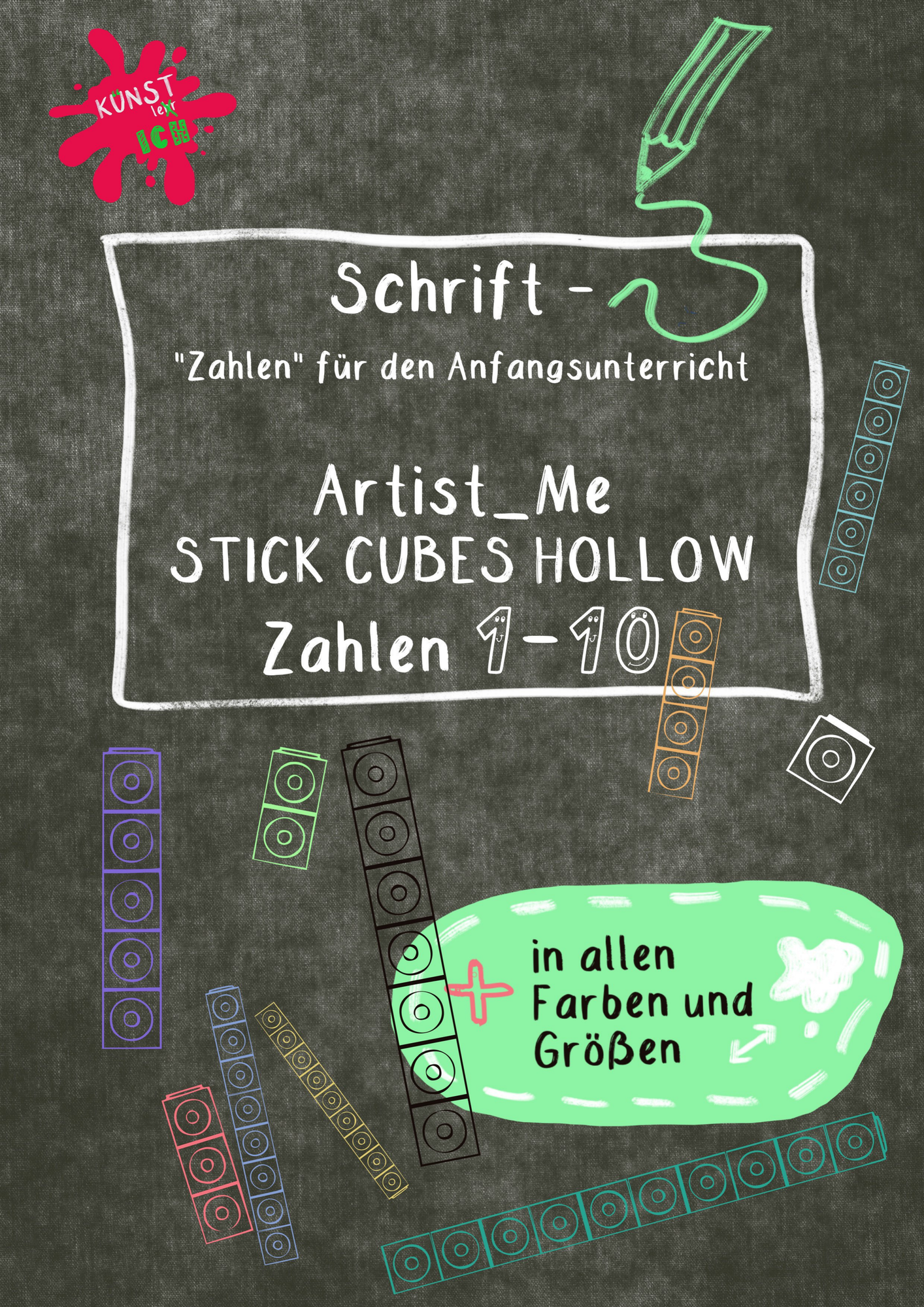
selbst erstellte Cliparts/Grafiken - Schrift / Ziffern / Font für den Anfangsunterricht - Steckwürfel - Artist Me - Stick Cubes Hollow - ART.ist_ME // Kuenstler_Ich - Deckblatt
Diese Schrift erleichtert die Gestaltung von Arbeitsblättern im Zahlenraum bis 10, 20 und 100.
Diese Steckwürfel sind lediglich in ihren Konturen deckend!
Da es keine 10 auf der Tastatur gibt, habe ich sie  dem Fragezeichen zugeordnet.
Schaue dir die beiden Beispielseiten an. Hier sieht man die Schrift in schwarz und weiß.
Schrift / Ziffern / Font für den Anfangsunterricht - Steckwürfel - Artist Me - Stick Cubes Hollow